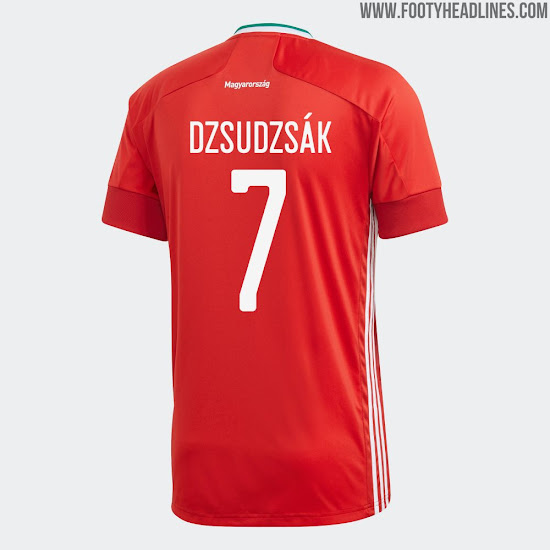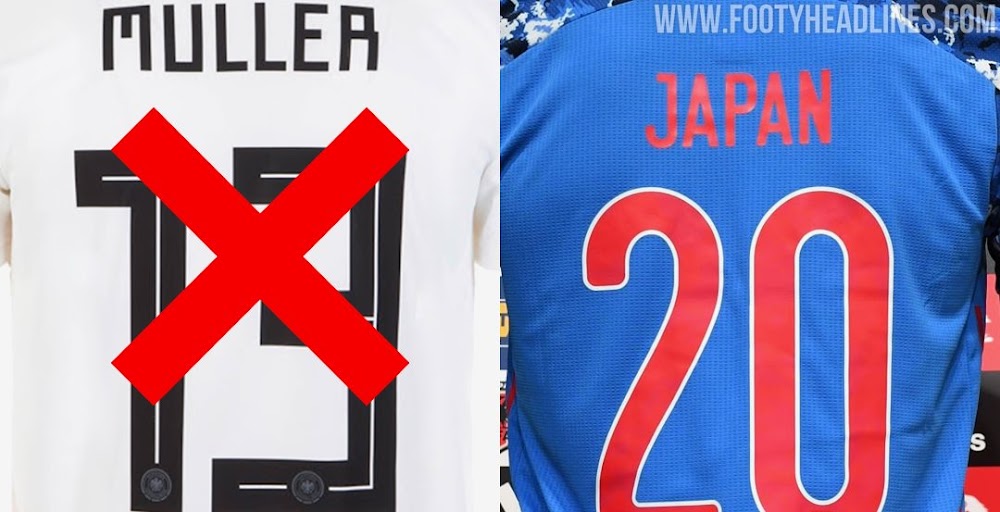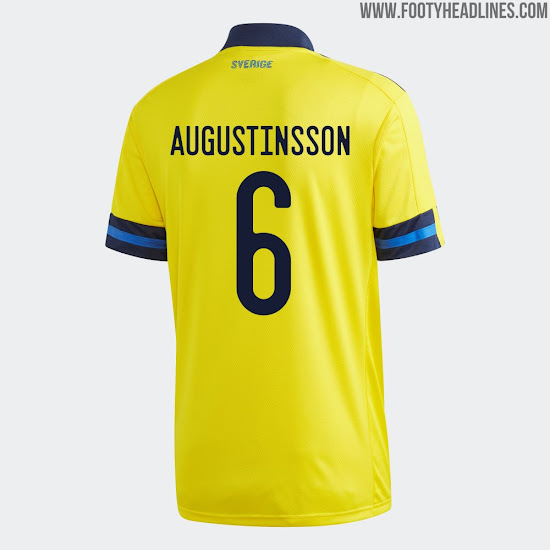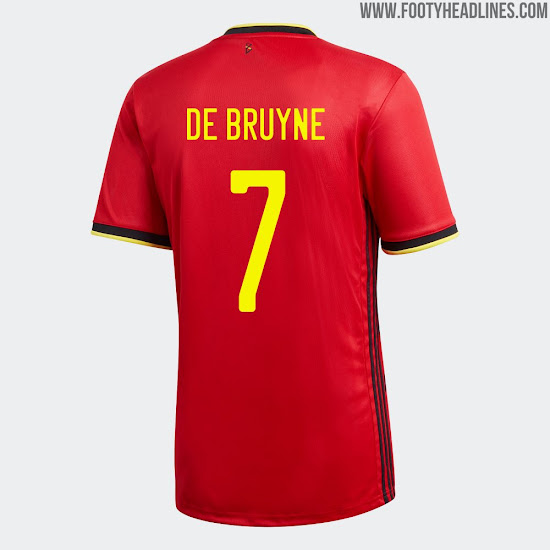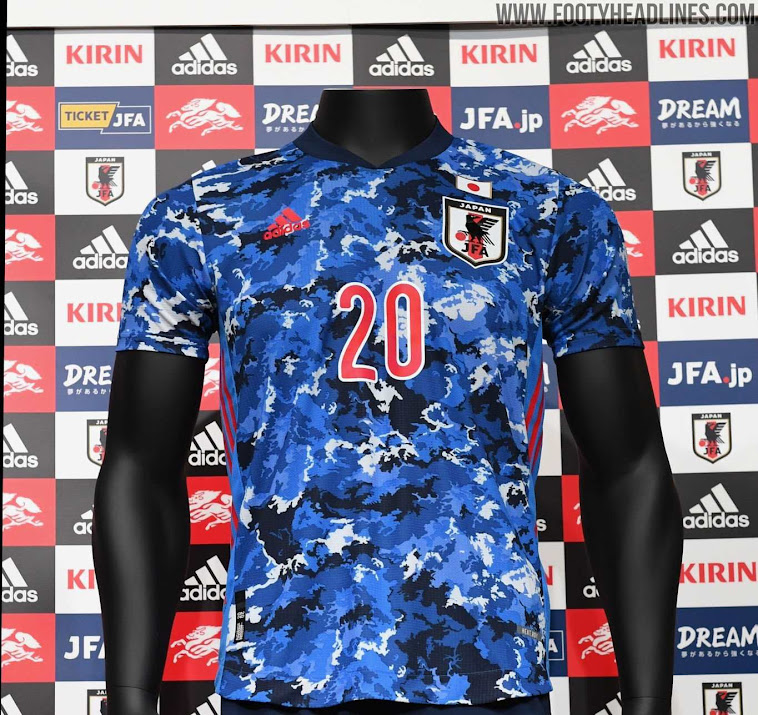
Brandneue Adidas (EM) 2020 Trikot-Schriftart enthüllt - sehr dezente, einzigartige Anpassung für jede Nation?
Update: Adidas hat die ersten ihrer EM 2020 / 2020-2021 Fußballtrikots veröffentlicht. Damit erhalten wir auch einen Blick auf die neue Adidas 2020 Schriftart - die Schriftart ist identisch für alle Teams, außer Deutschland.
Adidas 2020 Trikot-Schriftart - Wird bei EM 2020 von allen Teams außer Deutschland verwendet
Die neue Adidas 2020 Trikot-Schriftart weist eher einen Standard-Stil auf.
Interessanterweise verzichtet die Schriftart auf Adidas Produktbildern auf jegliche Anpassung. Jedoch sind wir uns ziemlich sicher, dass die Schriftarten aller Verbände zumindest das Verbandslogo am unteren Ende aufweisen werden.
Tatsächlich weist Japans 2020 Schriftart sogar ein subtiles Muster des Trikots auf. Es ist möglich, dass die Adidas-Schriftarten für die anderen Teams etwas ähnliches aufweisen werden - bleib für Bilder in Aktion dran.
Die neue Adidas 2020 Schriftart wird diese Woche von Adidas Nationalmannschaften debütiert.
Ursprünglicher Artikel - Japan / Brandneue Adidas (EM) 2020 Trikot-Schriftart enthüllt - sehr dezente, einzigartige Anpassung für jede Nation?
Mit der Veröffentlichung des neuen Japan 2020 Heimtrikots erhalten wir auch einen Blick auf die neue Adidas Fußballtrikot-Schriftart im Jahr 2020. Die neue Adidas 2020 Trikot-Schriftart soll im Jahr 2020 für alle Adidas Team-Trikots (u.a. EM 2020 & Copa America 2020) verwendet werden und ersetzt die berüchtigte Adidas WM 2018 Schriftart.
Adidas WM 2018 Schriftart sorgt erneut für Schlagzeilen
Die offizielle Adidas WM 2018 Schriftart sorgte durch ihre quadratischen Buchstaben und Zahlen im kyrillischen Stil für Verwirrung. Die WM 2018 Schriftart wurde von der traditionellen sowjetischen Bildsprache inspiriert.
Adidas 2020 Trikot Schriftart - wird für Copa America 2020 & EM 2020 verwendet
Die neue Adidas 2020 Trikot-Schriftart hat einen viel weniger irritierenden Stil als die WM 2018 Schriftart. Tatsächlich ist die Adidas 2020 Schriftart ziemlich genau sehr, sehr standardisiert. Die Zahlen und Buchstaben sind recht "schmal", vor allem im Vergleich zur 2018-Schriftart.
Das Interessanteste an der neuen Adidas 2020 Trikot Schriftart ist die Anpassung der Schriftart, die jedoch kaum sichtbar ist. Die Japan Adidas 2020 Schriftart setzt auf das gleiche Grafikmuster auf dem Trikot und das Verbandswappen am unteren Ende, die beide in Wirklichkeit sehr subtil sichtbar sind.
Weitere Beispiele für die neue Adidas 2020 Schriftart werden bald verfügbar sein, sobald die Drei Streifen in diesem Monat viele weitere Trikots für Nationalmannschaften herausbringen werden.